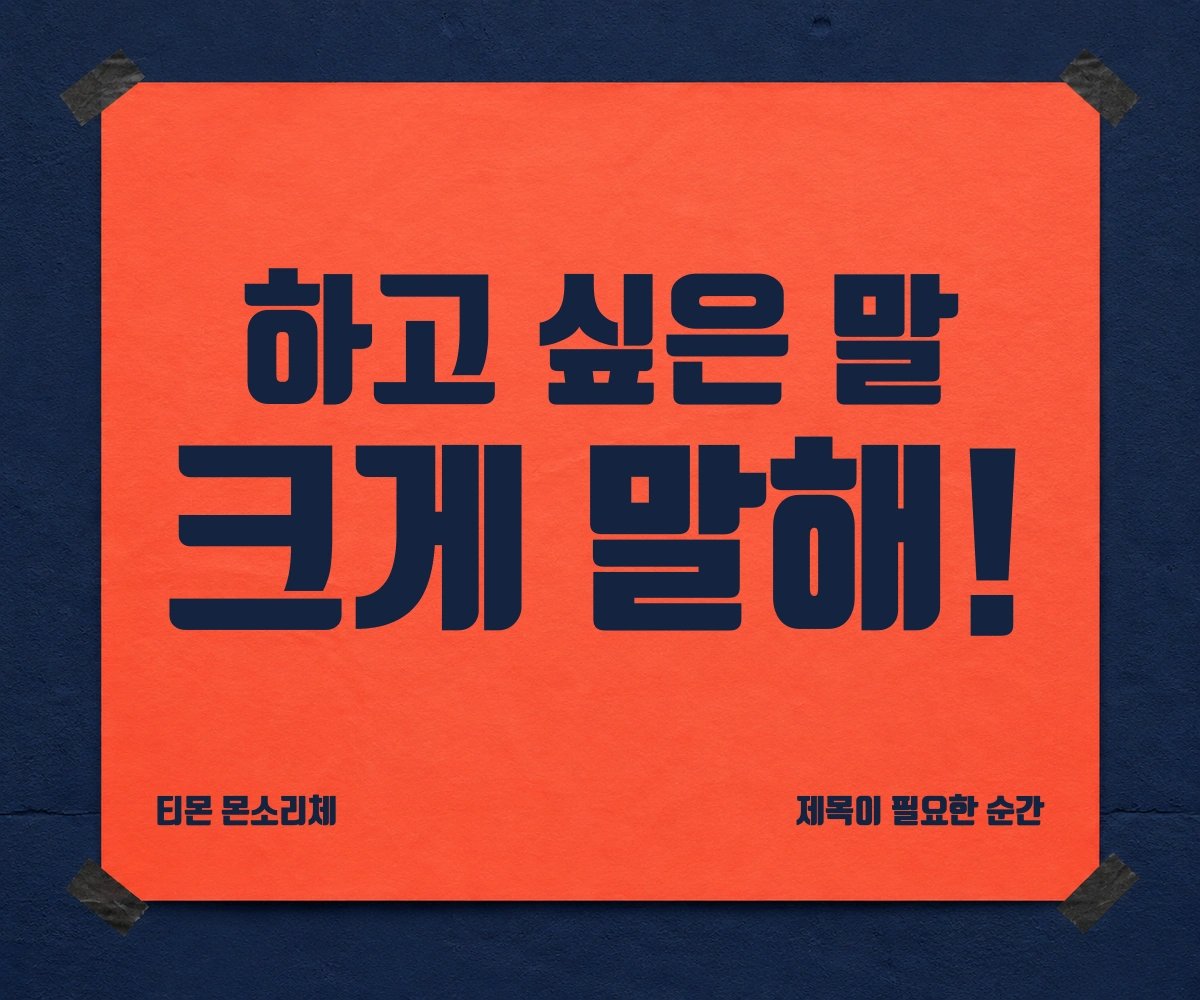
티몬 몬소리체 — 티몬에서 배포하는 무료 폰트입니다. 네모를 꽉 채우고 획 끝만 둥글린 제목용 서체
티몬이 2016년 7월에 공개한 전용 서체로 폰트릭스와 함께 만들었습니다. 국내 이커머스 기업 가운데 가장 먼저 개발한 기업 전용서체로 알려져 있습니다.
이름의 몬소리가 무슨 뜻인지가 이 서체의 배경입니다. 티몬의 몬과 목소리를 합친 말이 아니라 몬스터의 소리입니다. 제작사는 고객이 쇼핑하다 불편함을 겪거나 짜증이 날 때 무심결에 작은 소리로 중얼거리는 소리를 몬스터의 소리, 곧 몬소리로 정의했고, 그 목소리를 경청하겠다는 캠페인의 일환으로 서체를 만들었습니다.
제작사가 밝힌 조형은 부드러운 굴림과 임팩트 있는 굵기가 공존한다는 것입니다. 제목용으로 쓰기 좋은 두터운 느낌을 살리면서 부드러운 굴림을 적용했다고 설명합니다. 실제로 파일을 재어 보면 자면을 채우는 비율이 높은 편이라 존재감이 큽니다. 영문 전용인 티움체가 함께 배포되고, 2020년에 이름이 티몬체로 바뀌었습니다. 무료로 쓰고 수정과 재배포까지 가능합니다.